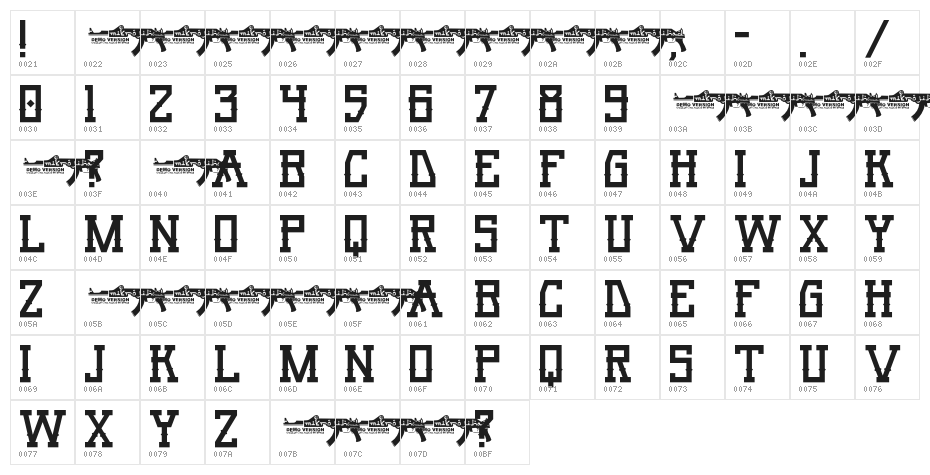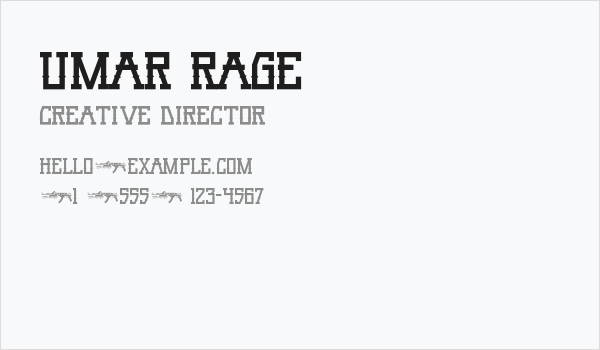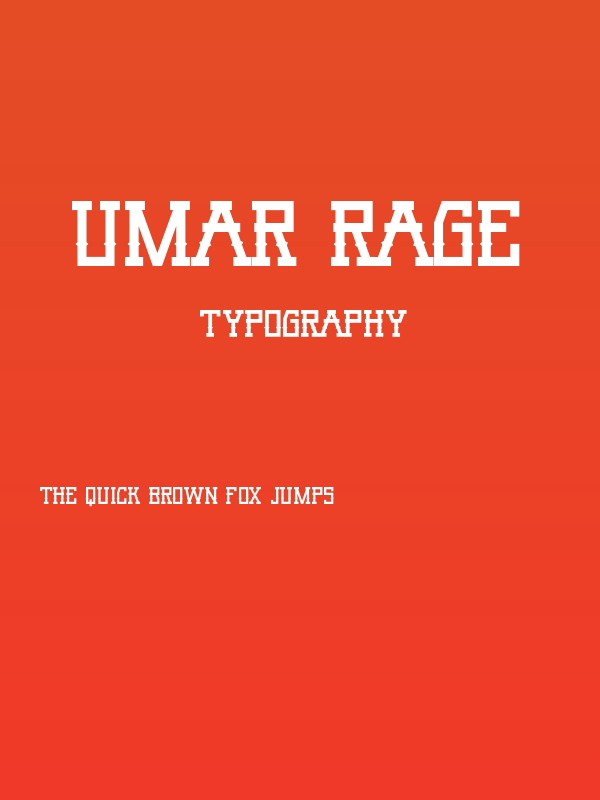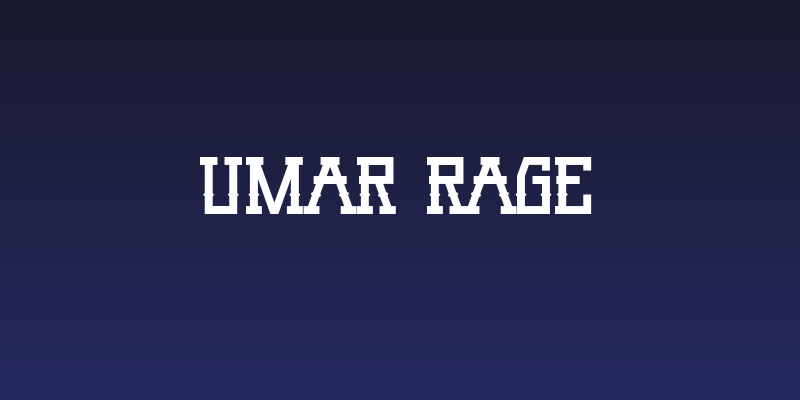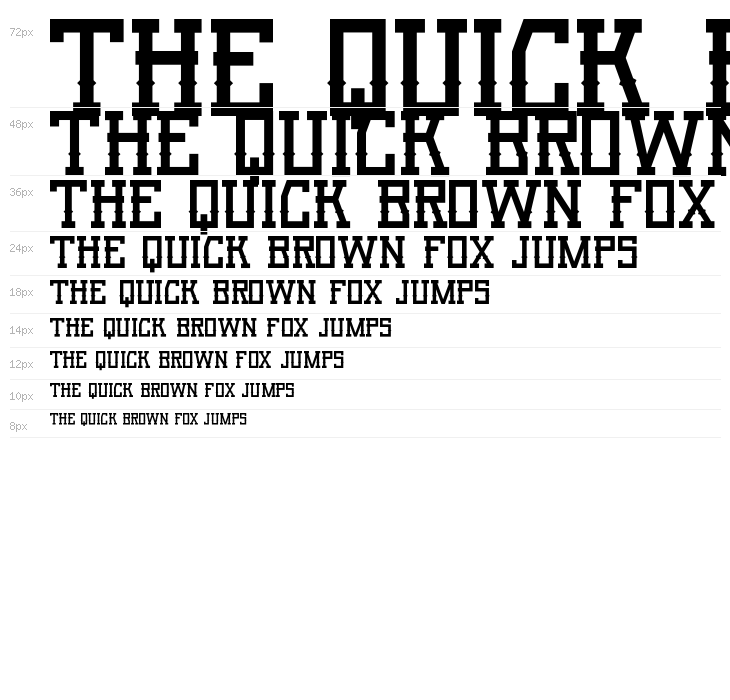
Umar Rage Font
| Progetti proposti | Ideal for posters, video game graphics, branding for tech or industrial companies, and any project needing a strong, bold typeface. |